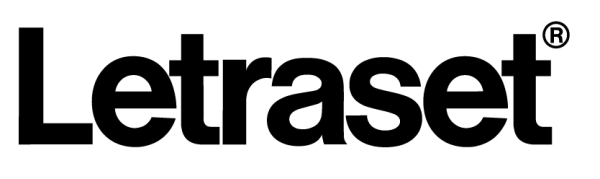
• Land: Großbritannien
• Ort: Ashford
• Status: nicht mehr aktiv
Letraset war ursprünglich ein Unternehmen aus Ashford (England), das insbesondere durch seine Abreibebuchstaben Bekanntheit erlangte, die ab Anfang der 1960er-Jahre verkauft wurden. Im Zuge des Ausbaus dieses Geschäftes entstanden auch viele namhafte Schriftentwürfe.
Die Marke gehört aktuell zur ColArt group. Es werden jedoch keine Schriften mehr entwickelt.